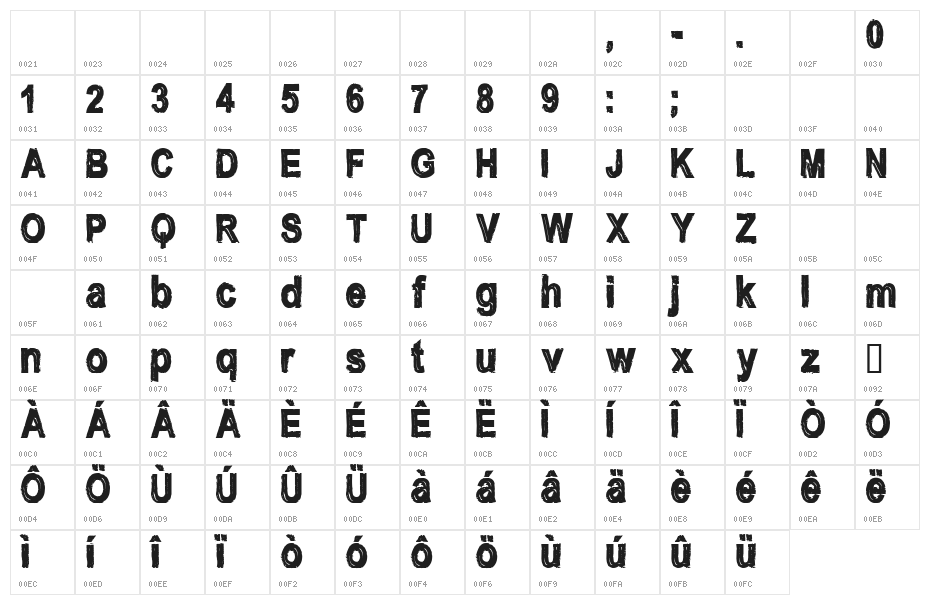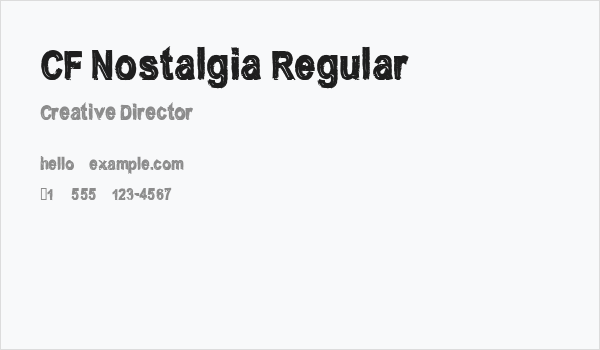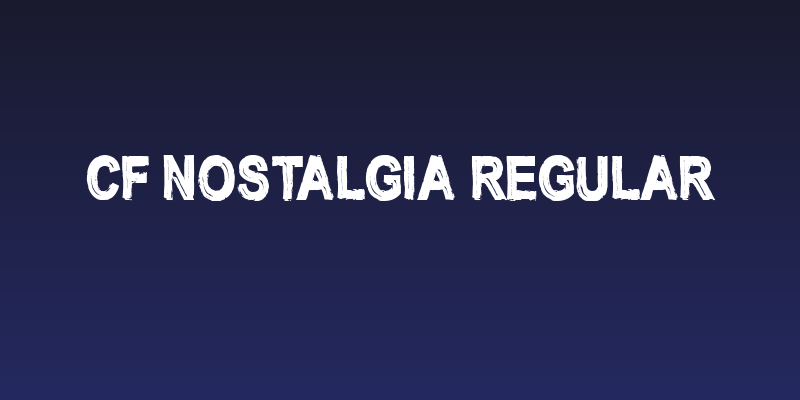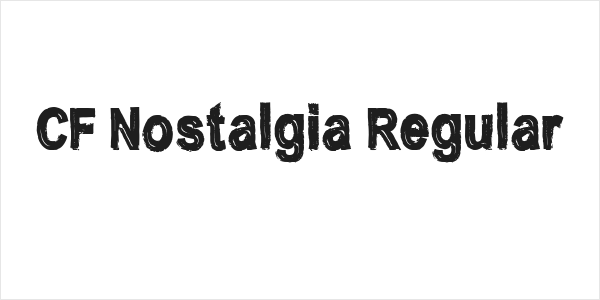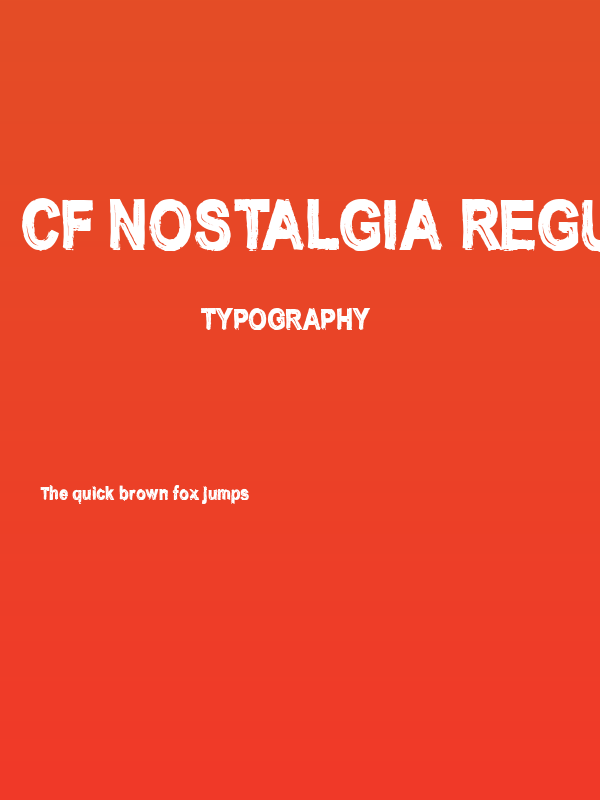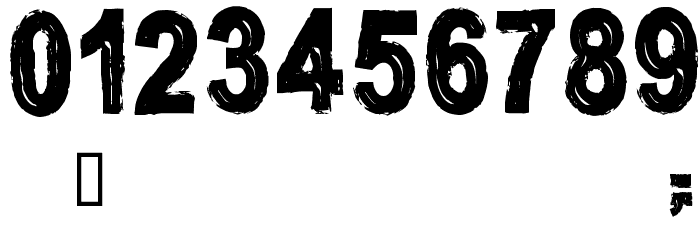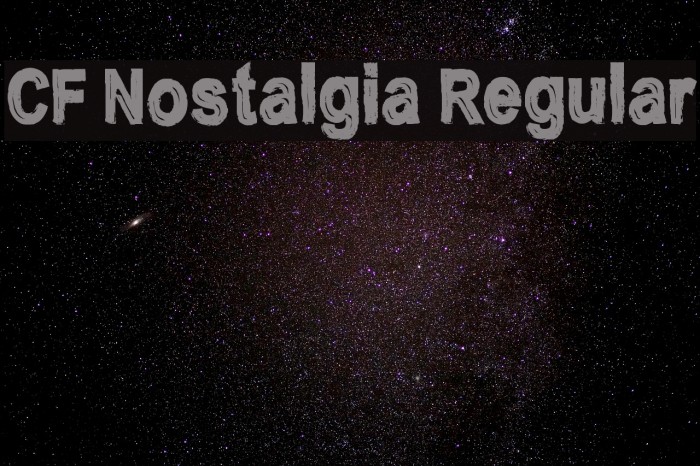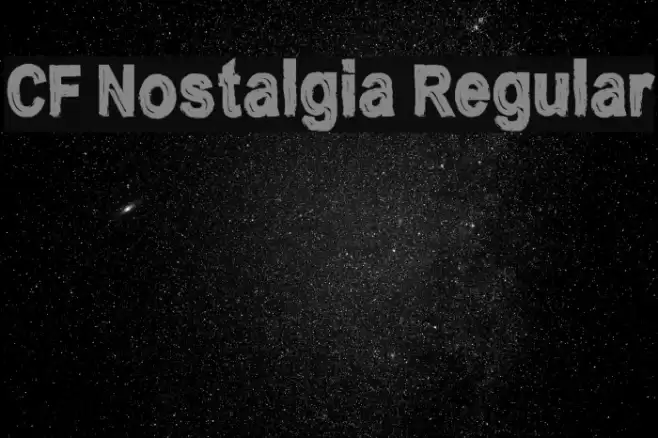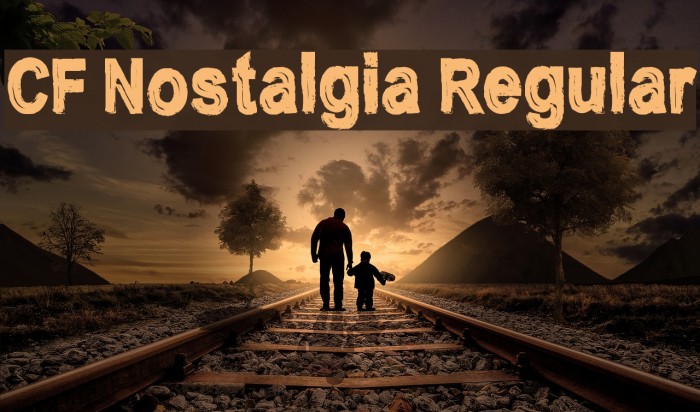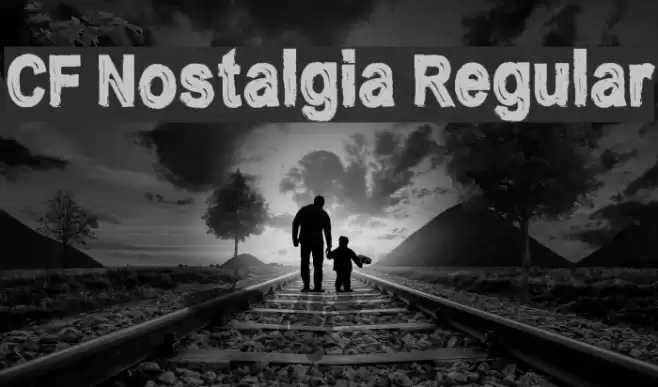
CF Nostalgia Regular Font
✎ Messy
| الفئات | Messy |
| النمط العام | Vintage |
| مشاريع مقترحة | Ideal for vintage posters, retro-themed branding, album covers, and any design needing a bold, nostalgic touch. |